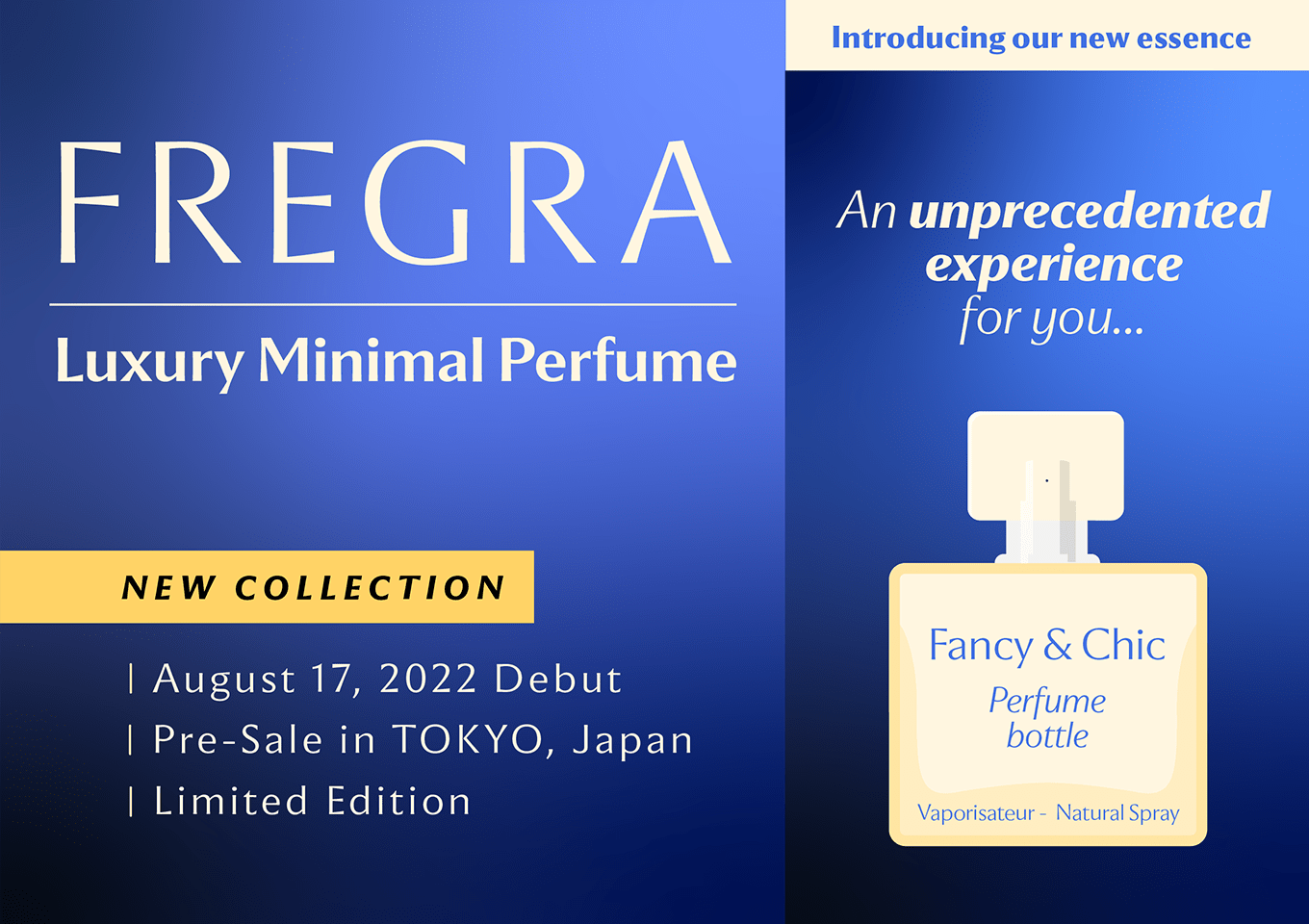
フィレンツェのルネサンス期碑文から着想を得たサンセリフ体です。ハイコントラストでフレア(先端にかけて広がっていくようなエレメント形状)なデザインが特徴的です。 サイズ別に最適化された、TextとDisplayの2つのバリエーションが用意され、本文利用を想定して設計されたTextはややコントラストを抑えることで可読性と気品を兼ね備えたデザインです。